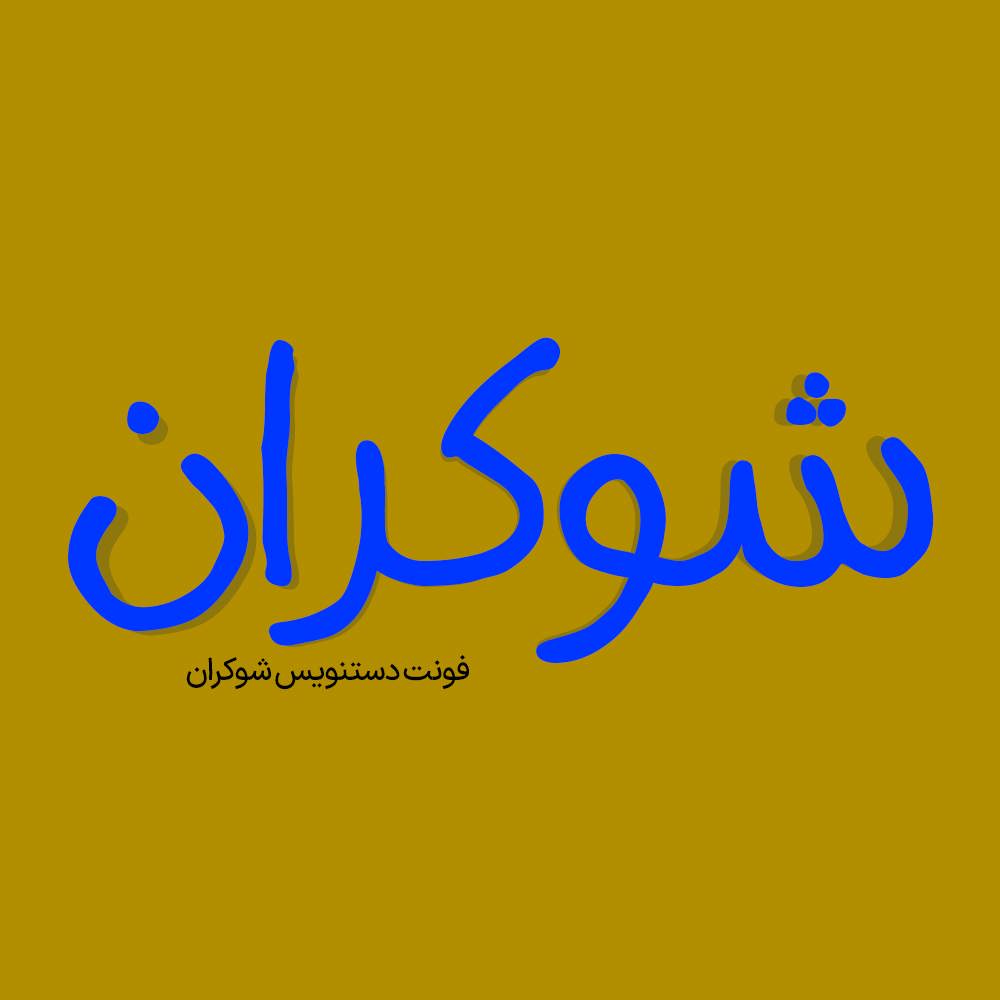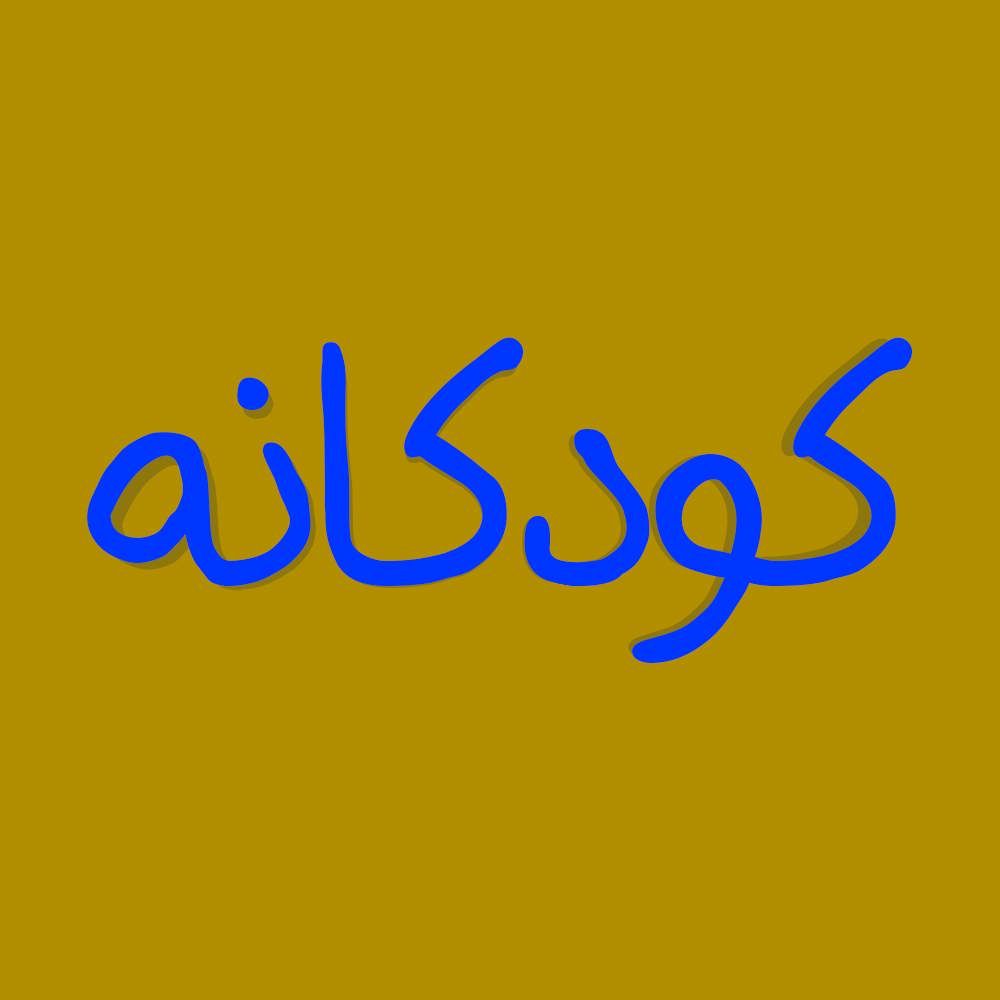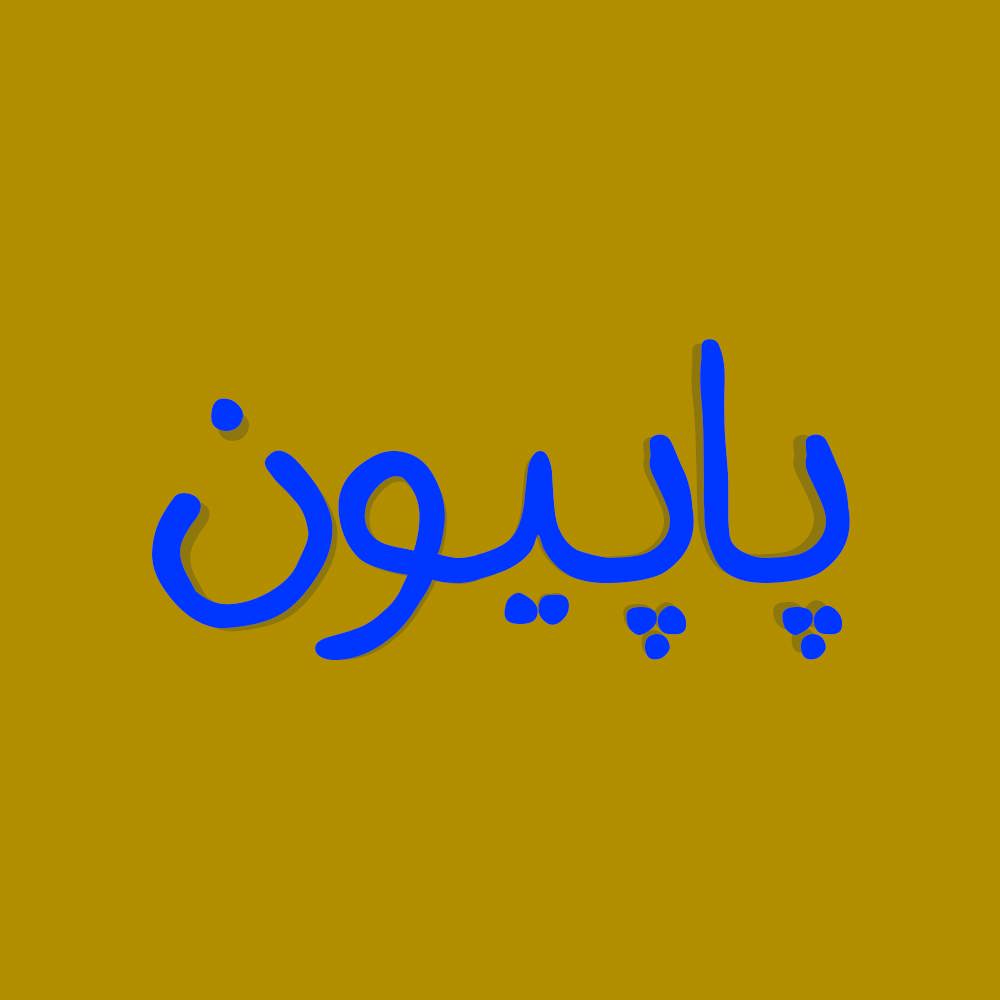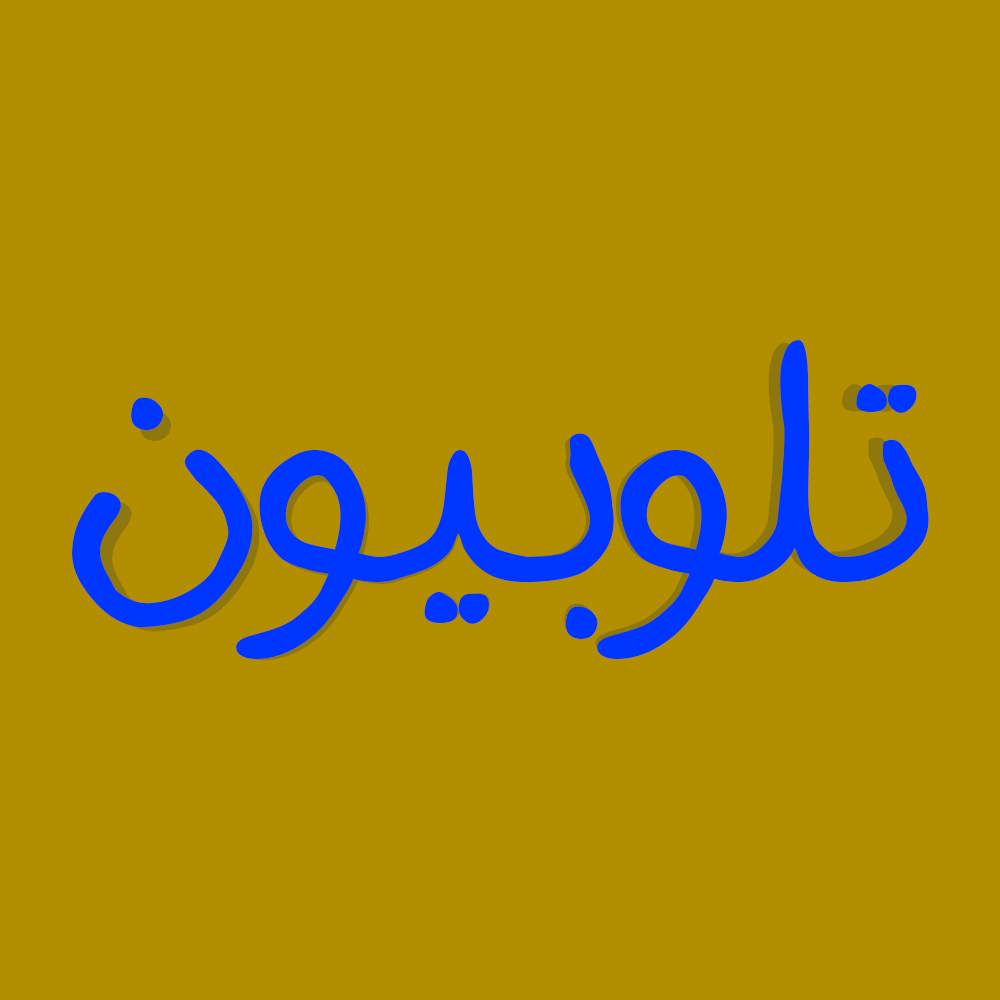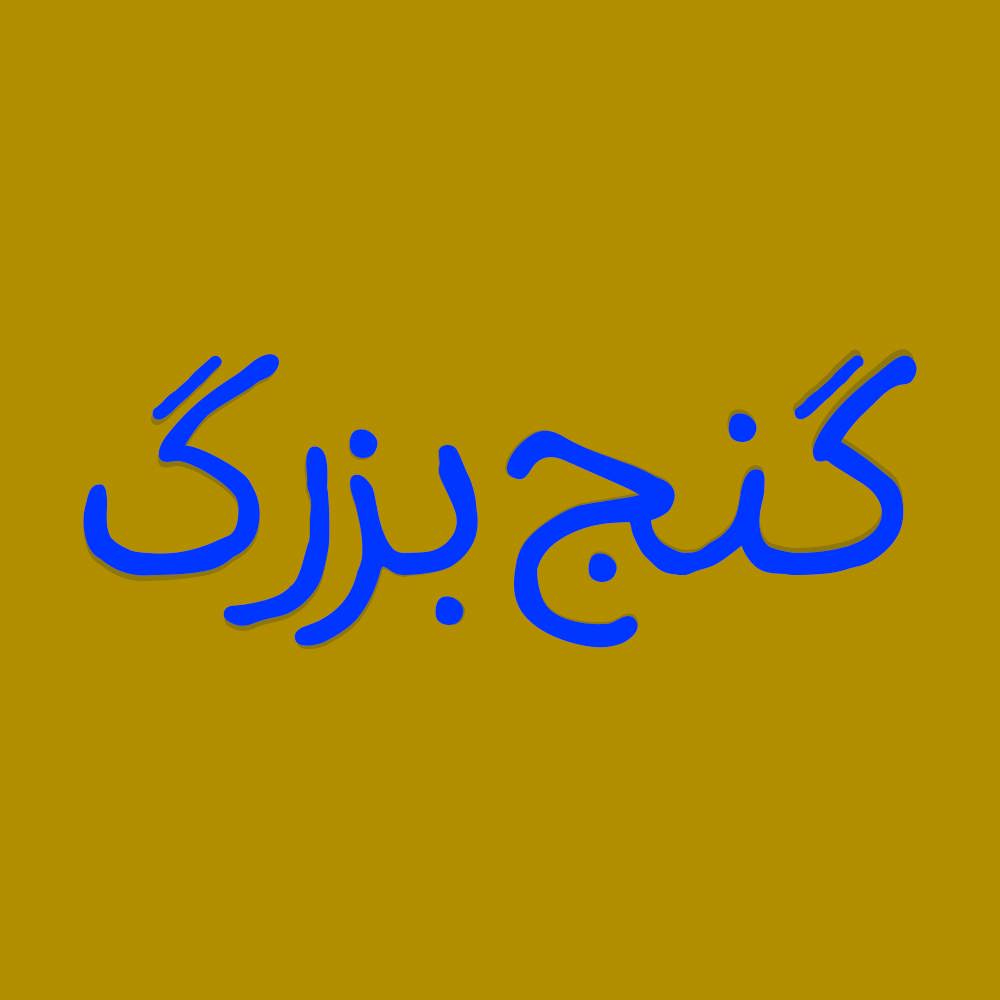
فونت فارسی شوکران Shokaran Font
فونت دستنویس شوکران از سری فونتهای فارسی دستنویس می باشد که مناسب برای استفاده در قسمت های خاص از تبلیغات، طراحی عکس نوشته ها و ایجاد فضای گرم و صمیمی در گرافیک کاربرد دارد.
فونت دستنویس شوکران یک فونت عربی، فارسی سازی و بهینه شده است که برای طراحی انواع امور گرافیکی به خصوص طراحی انواع لوگوتایپ و تایپوگرافی می باشد. از آنجایی که فونت هایی عربی فاقد حروف “گچ پژ” هستند و مشکلاتی در تایپ حروف “ک” و “ی” دارند در فونت شوکران حروف “گچ پژ” و همچنین اعداد فارسی و انگلیسی اضافه شده است تا بتوانید تمامی متن فارسی را به وسیله این فونت تایپ کنید. در ادامه برای شما نمونه تایپ های این محصول حرفه ای رو آماده کردیم که میتونید مشاهده کنید.
پیشنمایش و نمونه تایپ های فونت شوکران